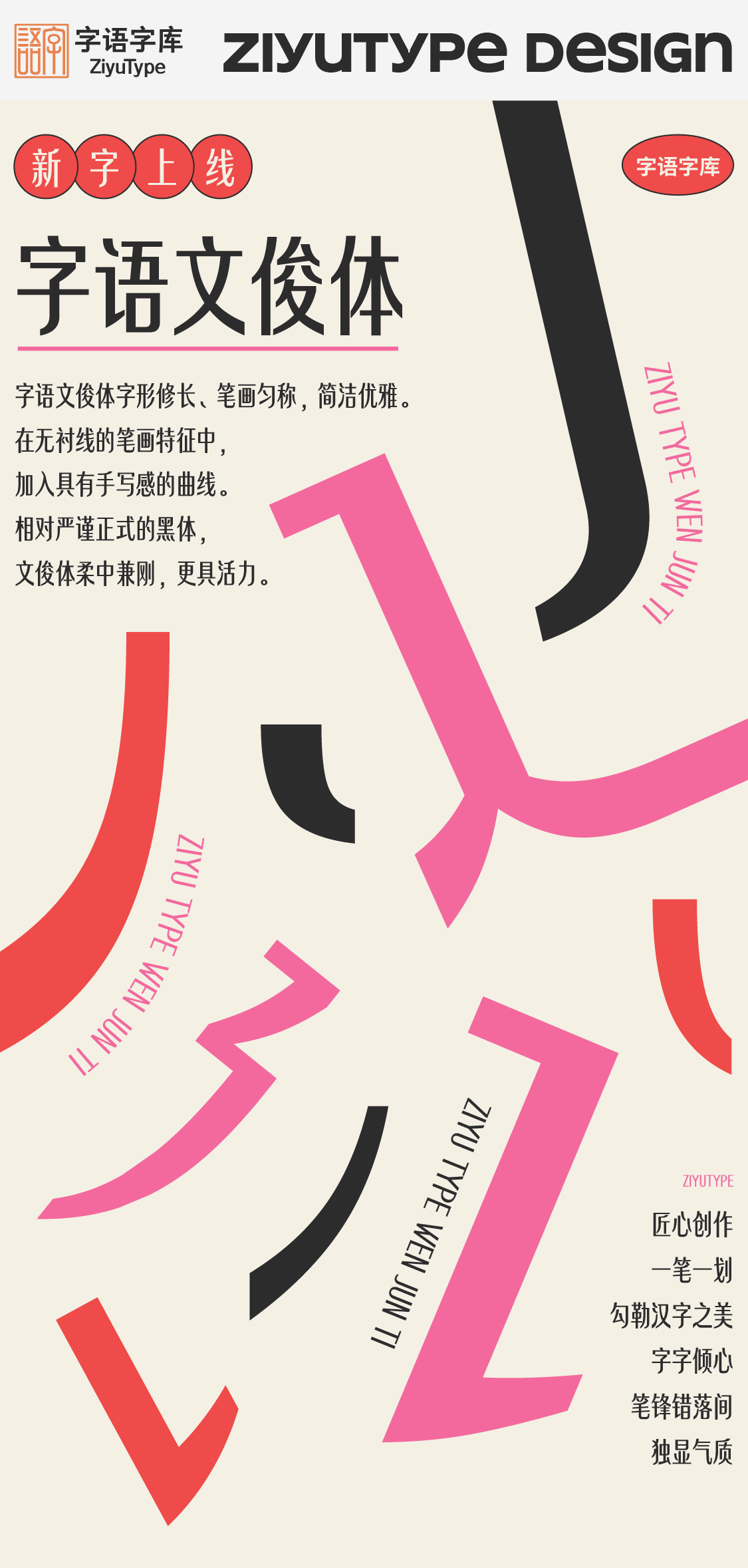
《字语文俊体》以其修长的字形、匀称的笔画和简洁的结构,展现出一种优雅沉稳的视觉秩序。它不繁不冗,却有一种内敛的张力。
《字语文俊体》专为广告、包装、影视、标题等领域量身打造,适配各种设计场景。
在花哨与极简之间,《字语文俊体》找到了一种恰到好处的表达方式。它不拘于传统宋黑的框架,也不流于网红手写的轻浮,而是以独到的风格,在视觉世界中稳稳立足。